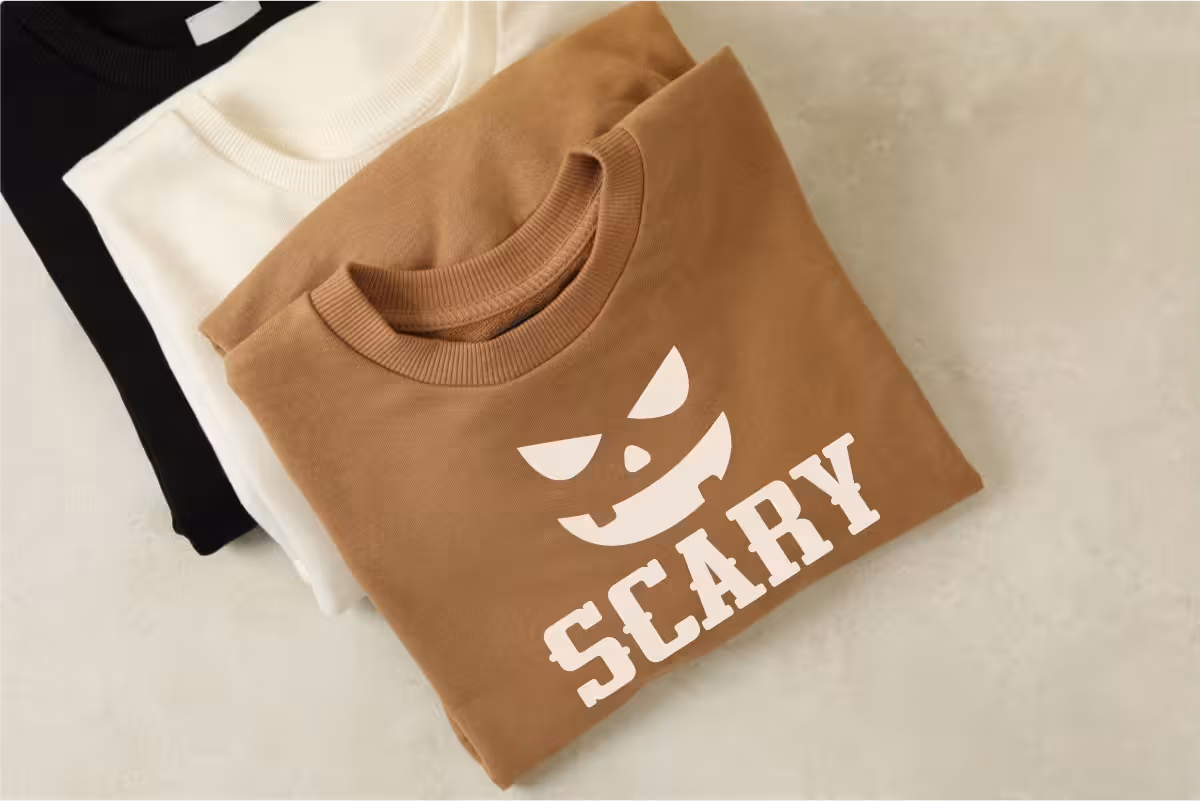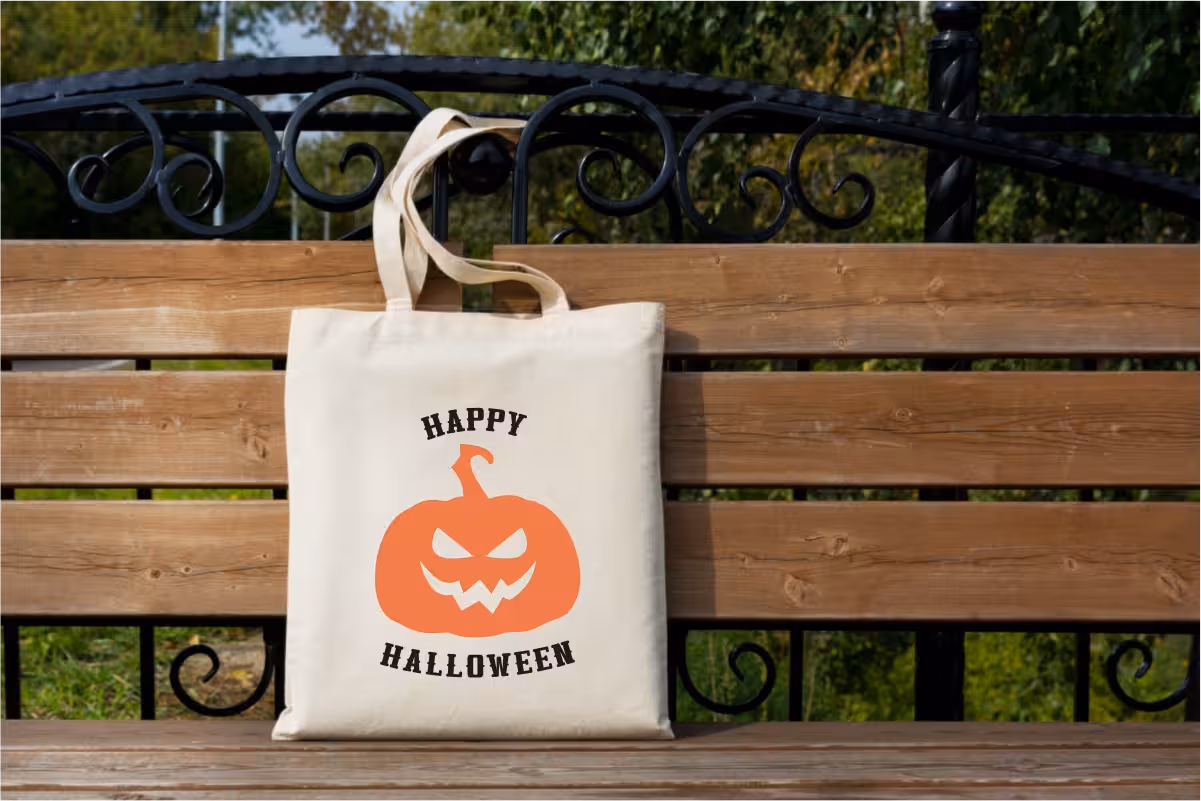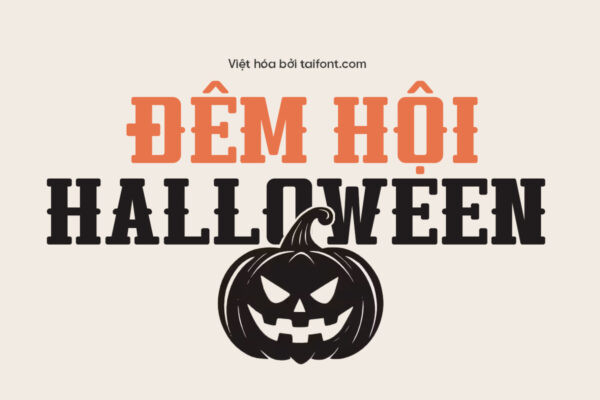
Giới thiệu về Font TF Spooky Vibes Việt hóa
TF Spooky Vibes Việt hóa là một font chữ đặc biệt, được thiết kế để mang đậm phong cách Halloween, tạo cảm giác ma mị, rùng rợn nhưng vẫn đầy thú vị và cá tính. Font này toát lên vẻ bí ẩn, huyền ảo và một chút tinh nghịch, lý tưởng để tạo không khí đặc trưng của lễ hội ma quái và thu hút mọi ánh nhìn.
Với đặc điểm thiết kế độc đáo, góc cạnh hoặc uốn lượn đầy bí ẩn và khả năng gợi cảm xúc mạnh mẽ, Spooky Vibes là lựa chọn hoàn hảo cho các ấn phẩm trong mùa Halloween:
- Thiết kế Halloween: Hoàn hảo để sử dụng trên poster, banner, thiệp mời cho các bữa tiệc Halloween, sự kiện hóa trang, hoặc các chương trình đặc biệt trong dịp này. Font này giúp tạo không khí rùng rợn, kỳ bí và đầy mê hoặc, đúng chất Halloween.
- Thiết kế cho các sản phẩm liên quan đến kinh dị/giả tưởng: Lý tưởng cho tiêu đề sách, game, hoặc phim ảnh có chủ đề ma quỷ, phù thủy, hoặc các câu chuyện giả tưởng. Nét chữ độc đáo của font sẽ làm tăng tính chân thực và sự hấp dẫn cho nội dung.
- Thiết kế đồ dùng trang trí và quà tặng: Phù hợp cho nhãn mác sản phẩm, decal dán tường, hoặc các vật phẩm lưu niệm muốn mang phong cách Halloween độc đáo.
- Thiết kế truyền thông xã hội: Rất phù hợp cho các bài đăng, story trên mạng xã hội quảng bá các sự kiện Halloween, khuyến mãi theo chủ đề hoặc đơn giản là tạo không khí lễ hội.
Với TF Spooky Vibes Việt hóa, bạn có thể dễ dàng thổi hồn ma mị, sự độc đáo và cá tính vào các thiết kế, tạo ra những sản phẩm không chỉ đẹp mắt mà còn cực kỳ ấn tượng và có khả năng thu hút sự chú ý tối đa trong mùa Halloween.